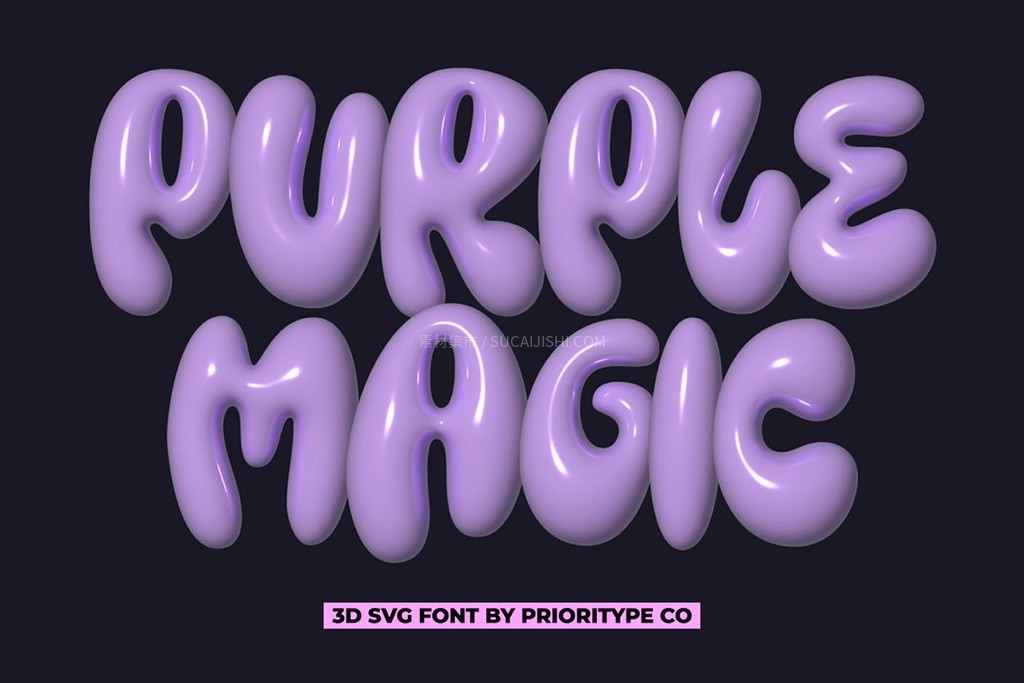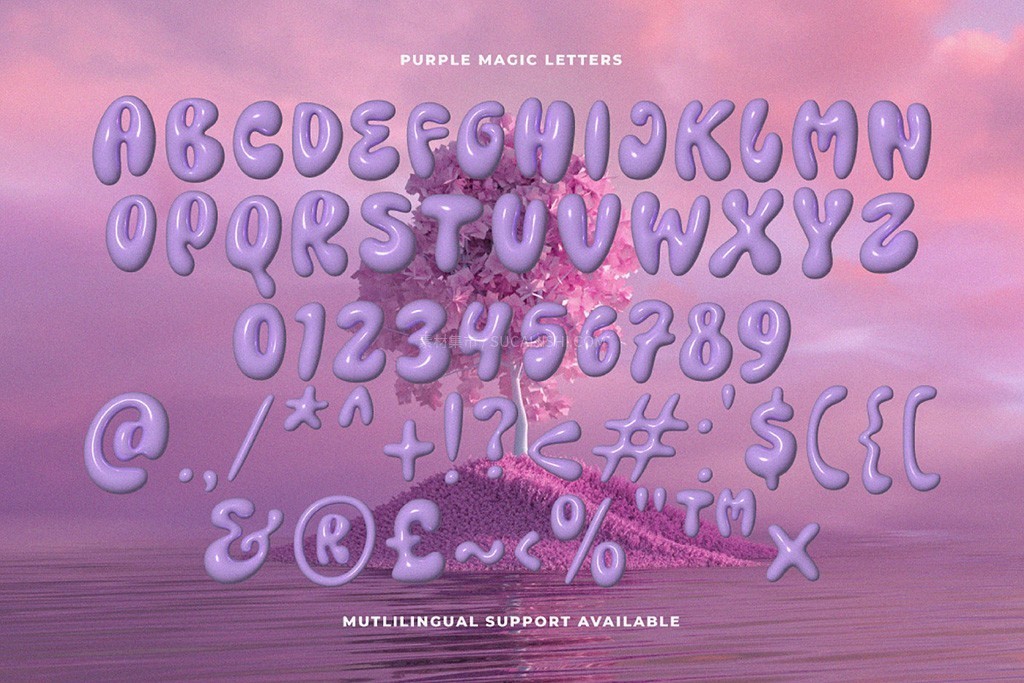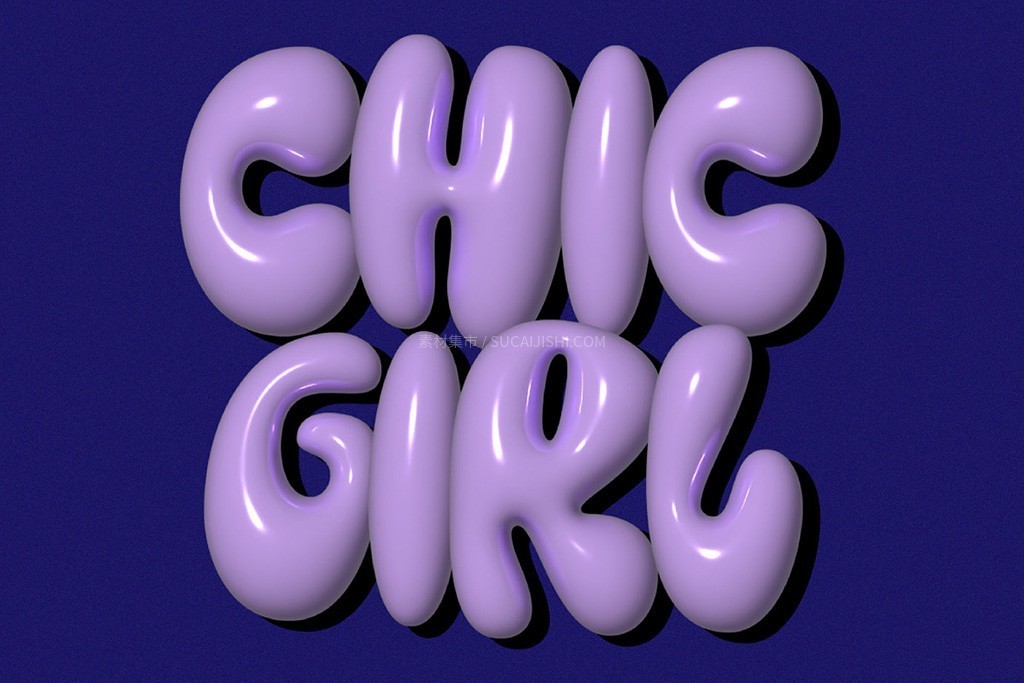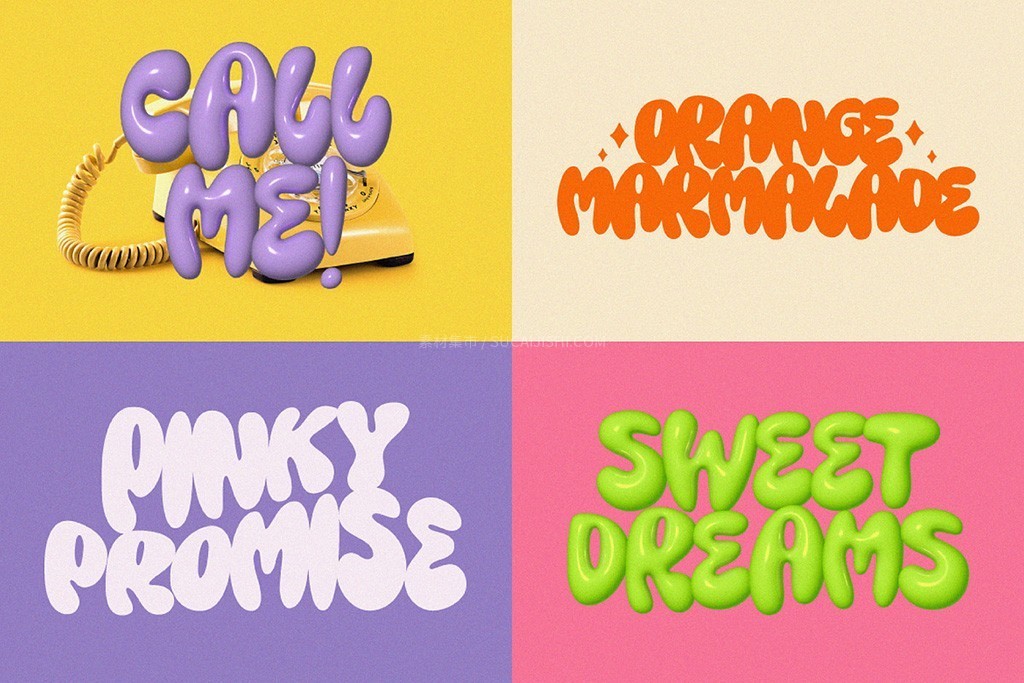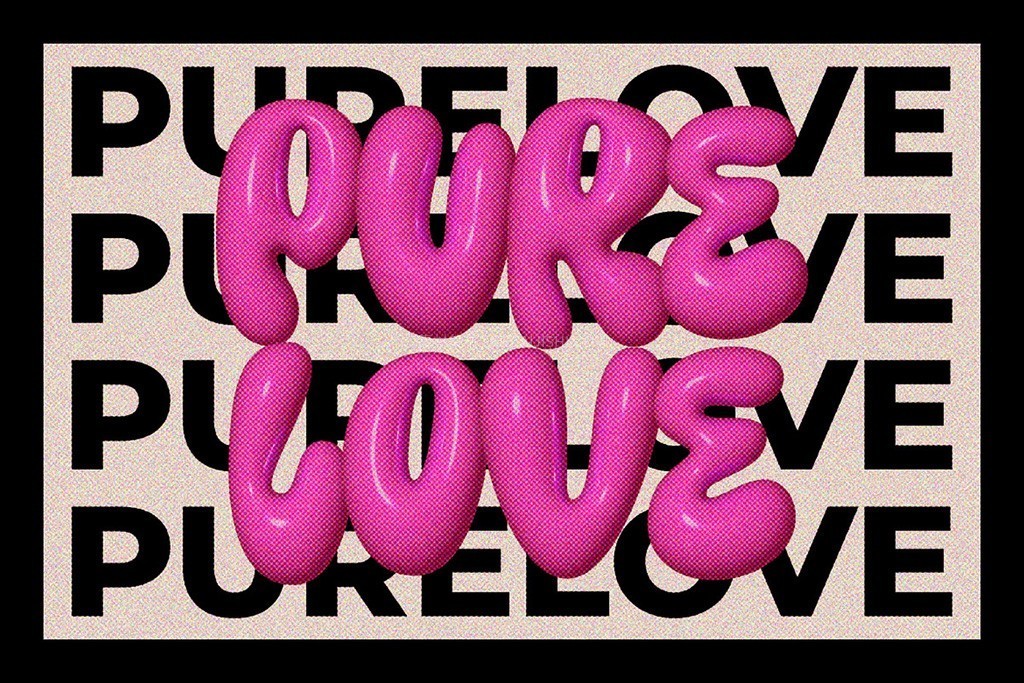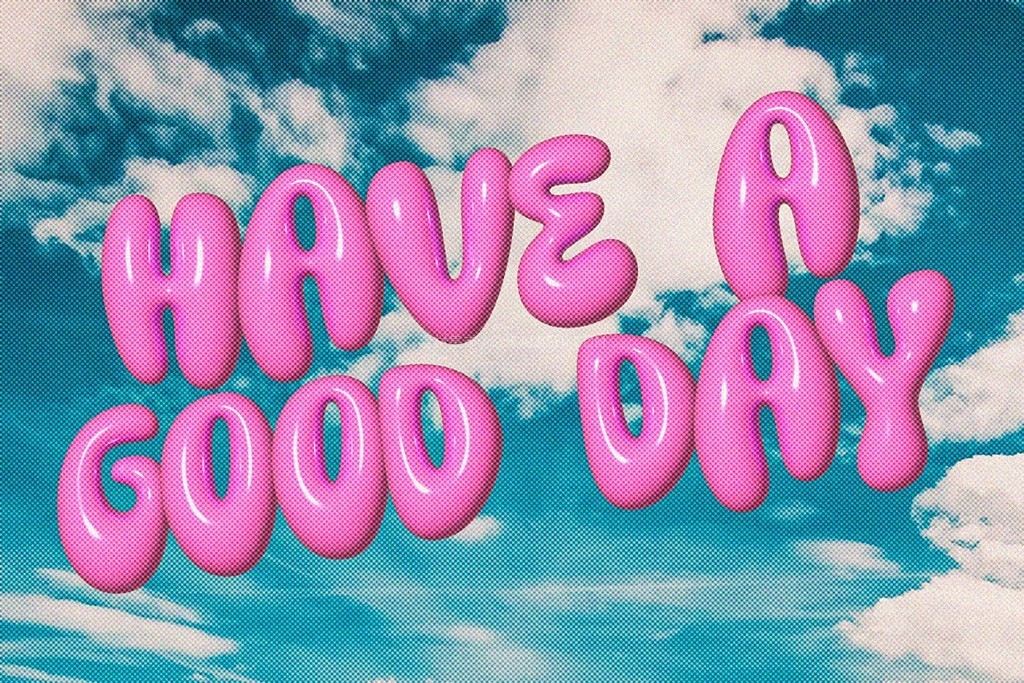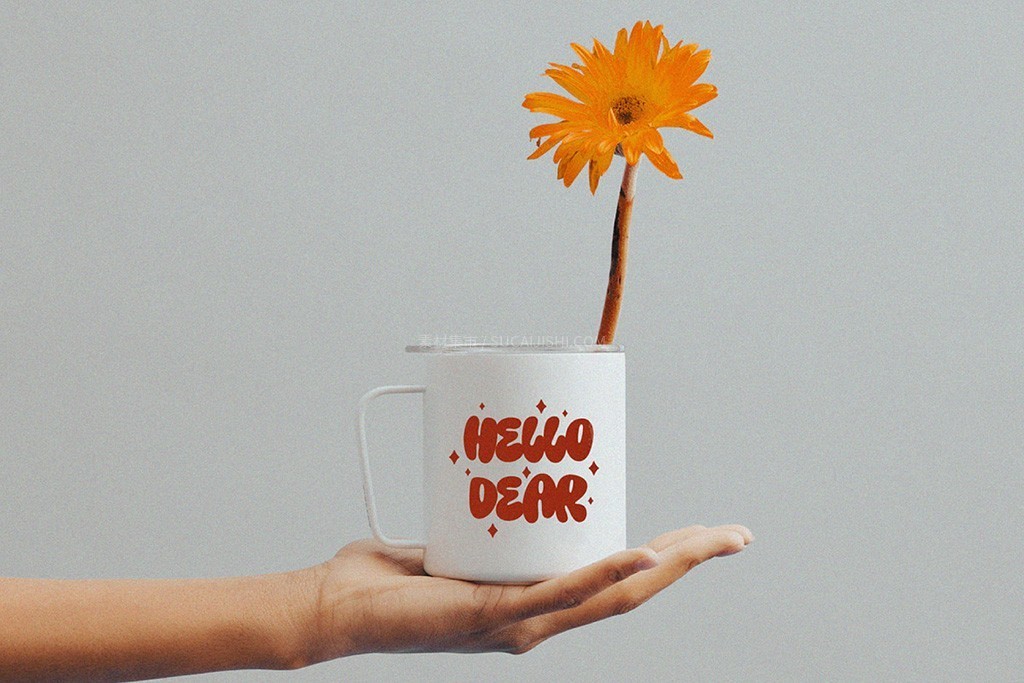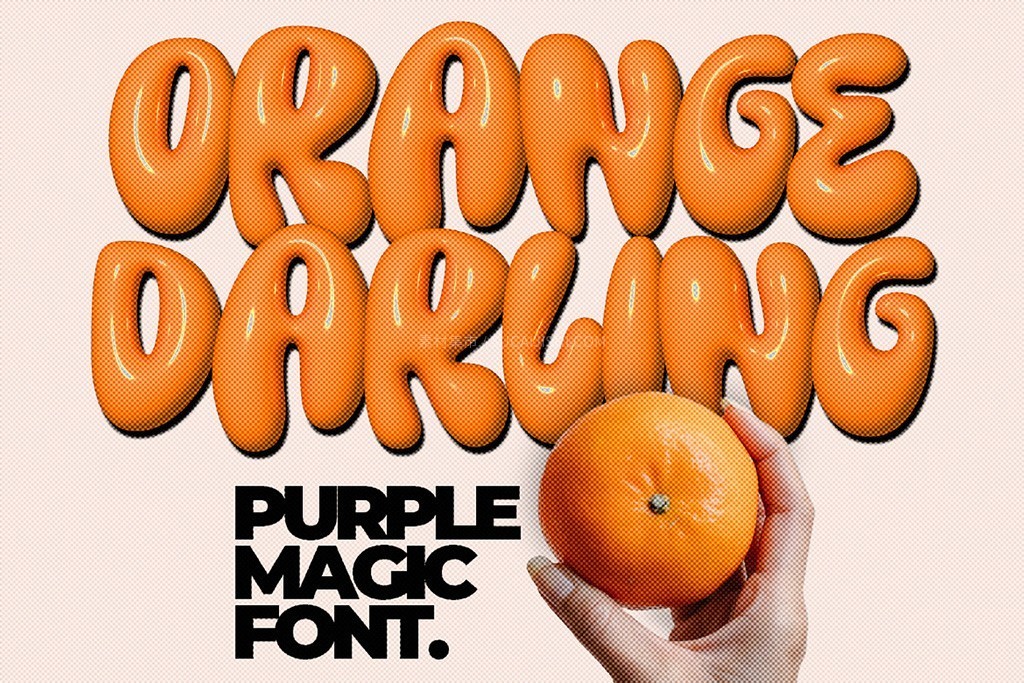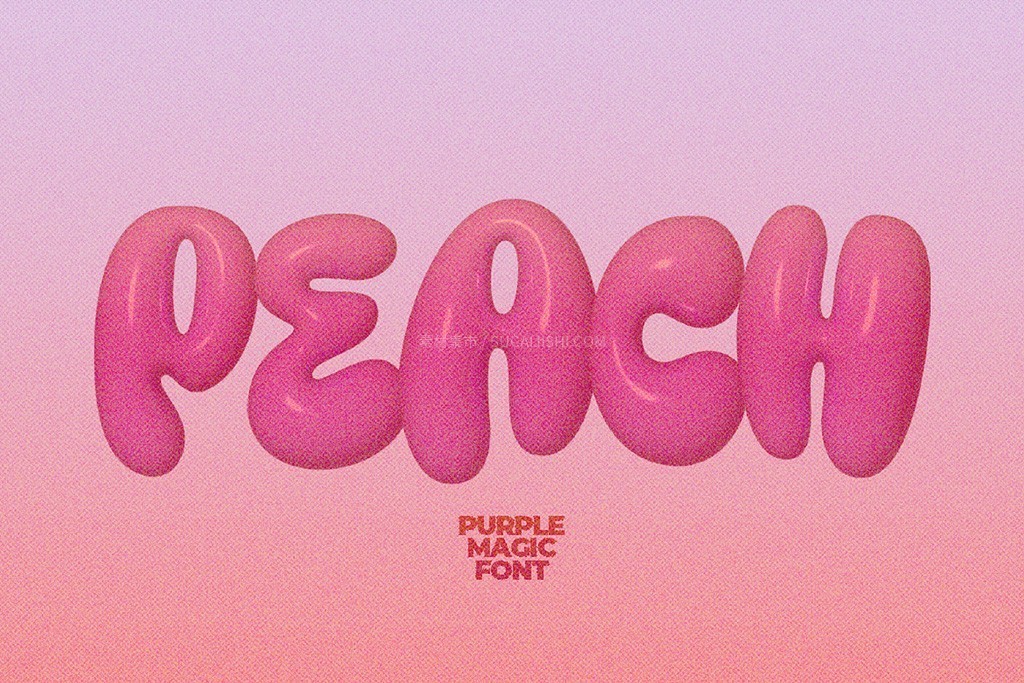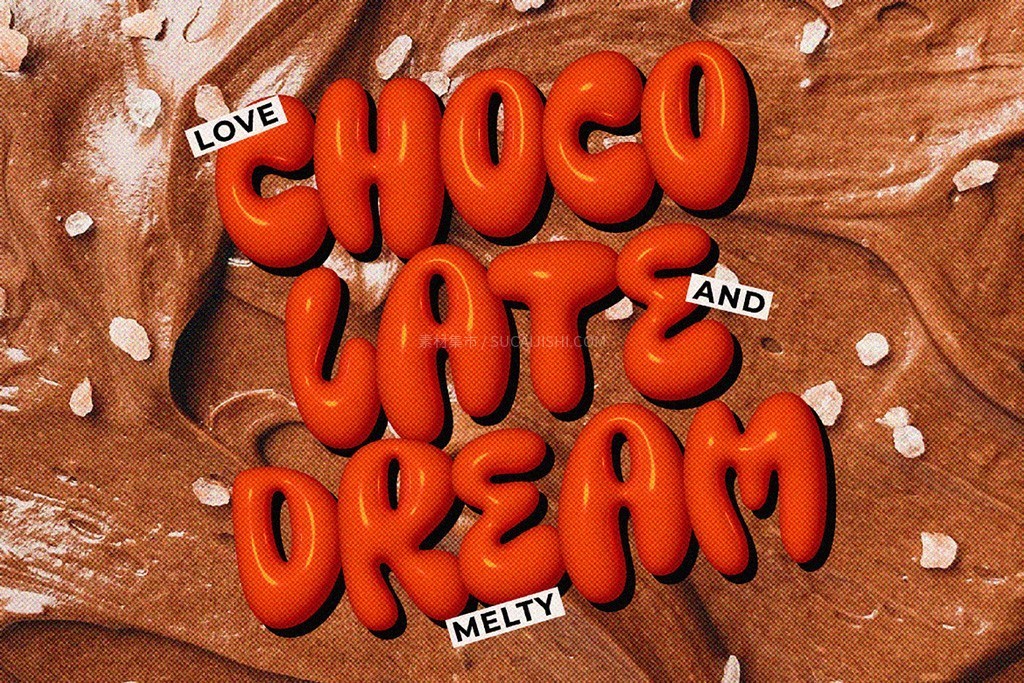
Purple Magic 3D膨胀位图字体
Purple Magic 是一款极具个性的3D膨胀位图字体,提供逼真的 3D SVG 和常规两种样式。该字体功能全面,包含大写字母、小写字母、数字、标点符号,并提供极其广泛的多语言支持(涵盖数十种语言)。您可以非常方便地在 Photoshop 中使用“色相/饱和度”或在 Illustrator 中通过“色彩平衡”来自由更改字体颜色。素材包内含 OTF、TTF 和 WOFF 格式,全面满足桌面与网页设计需求。